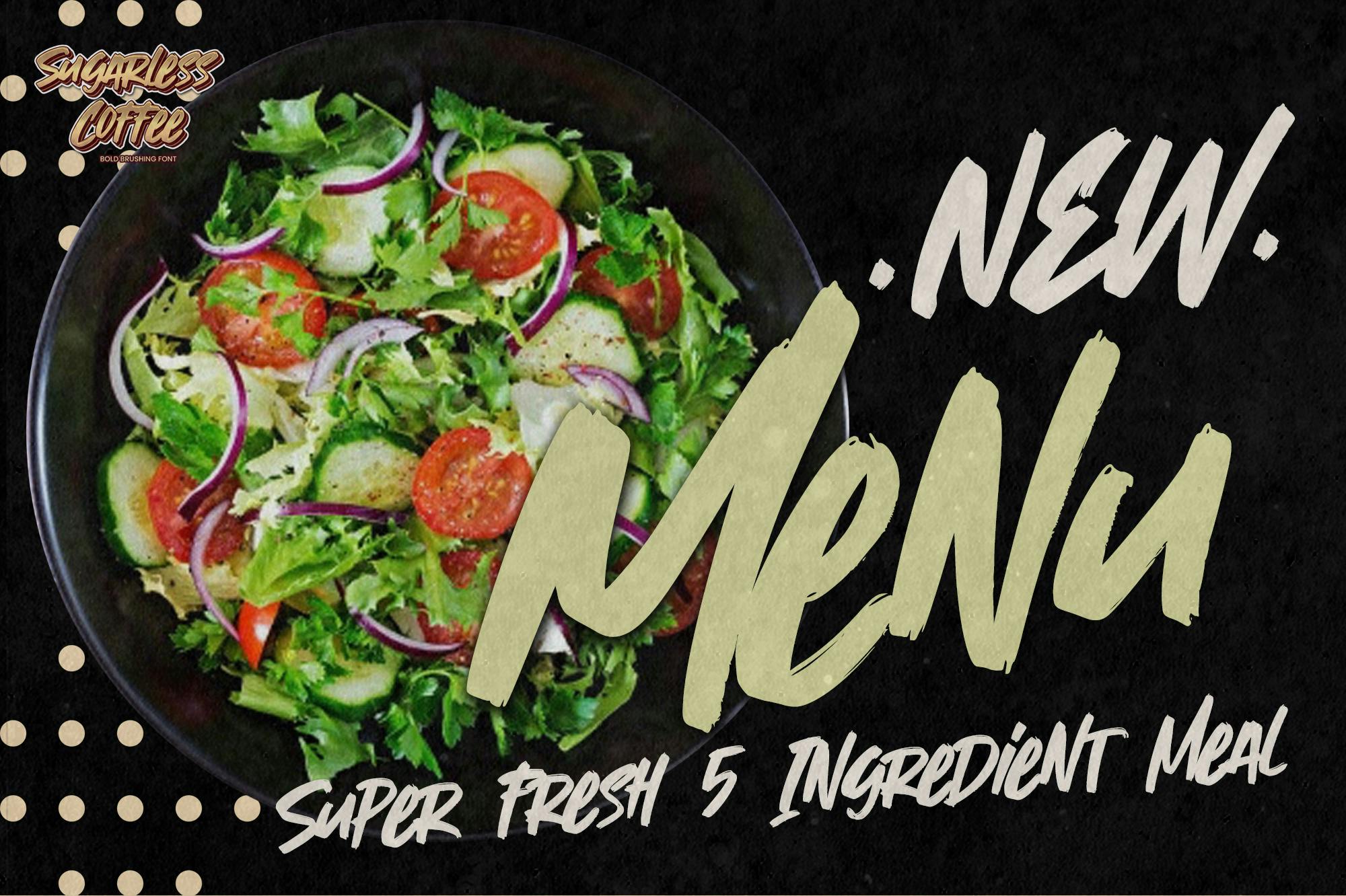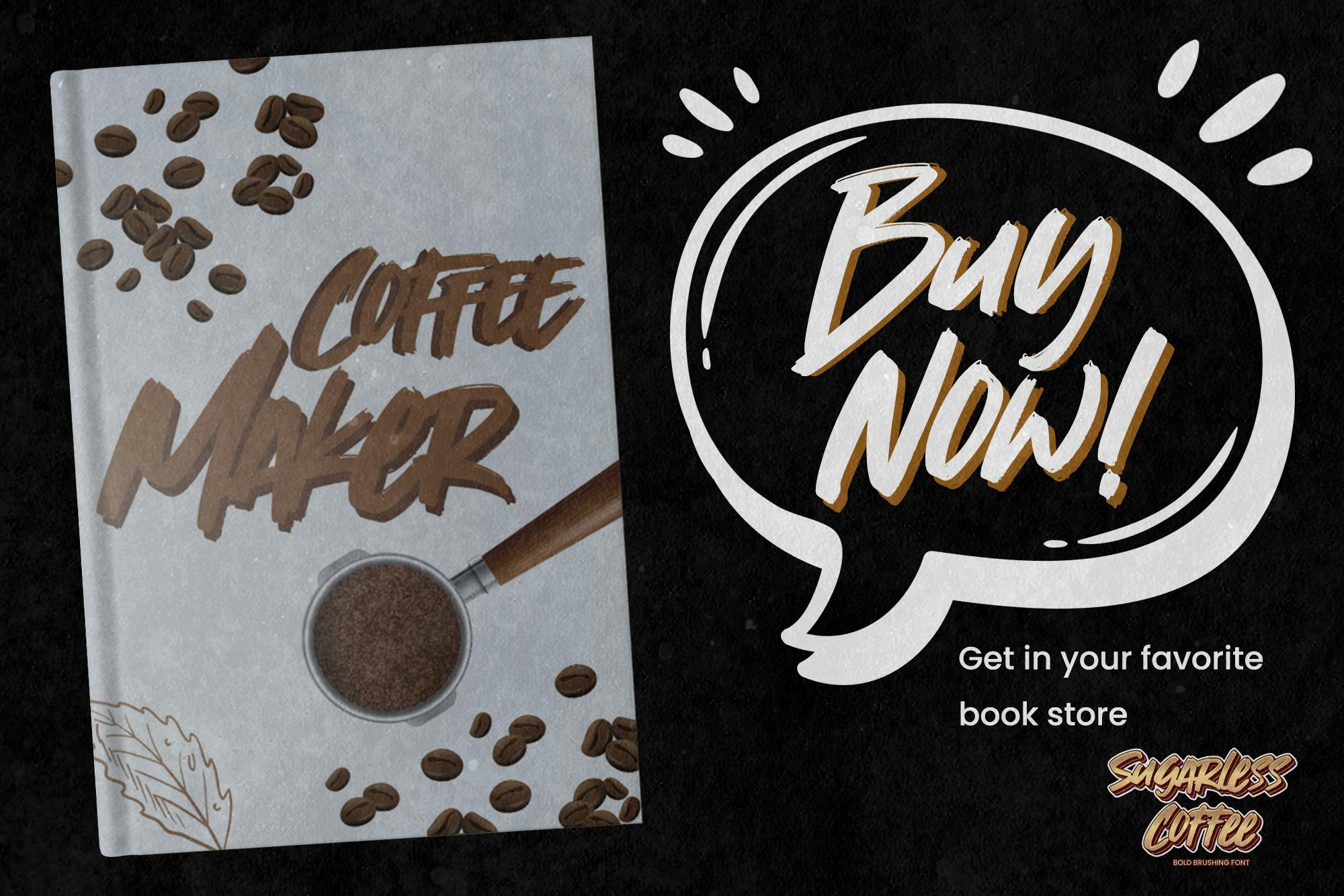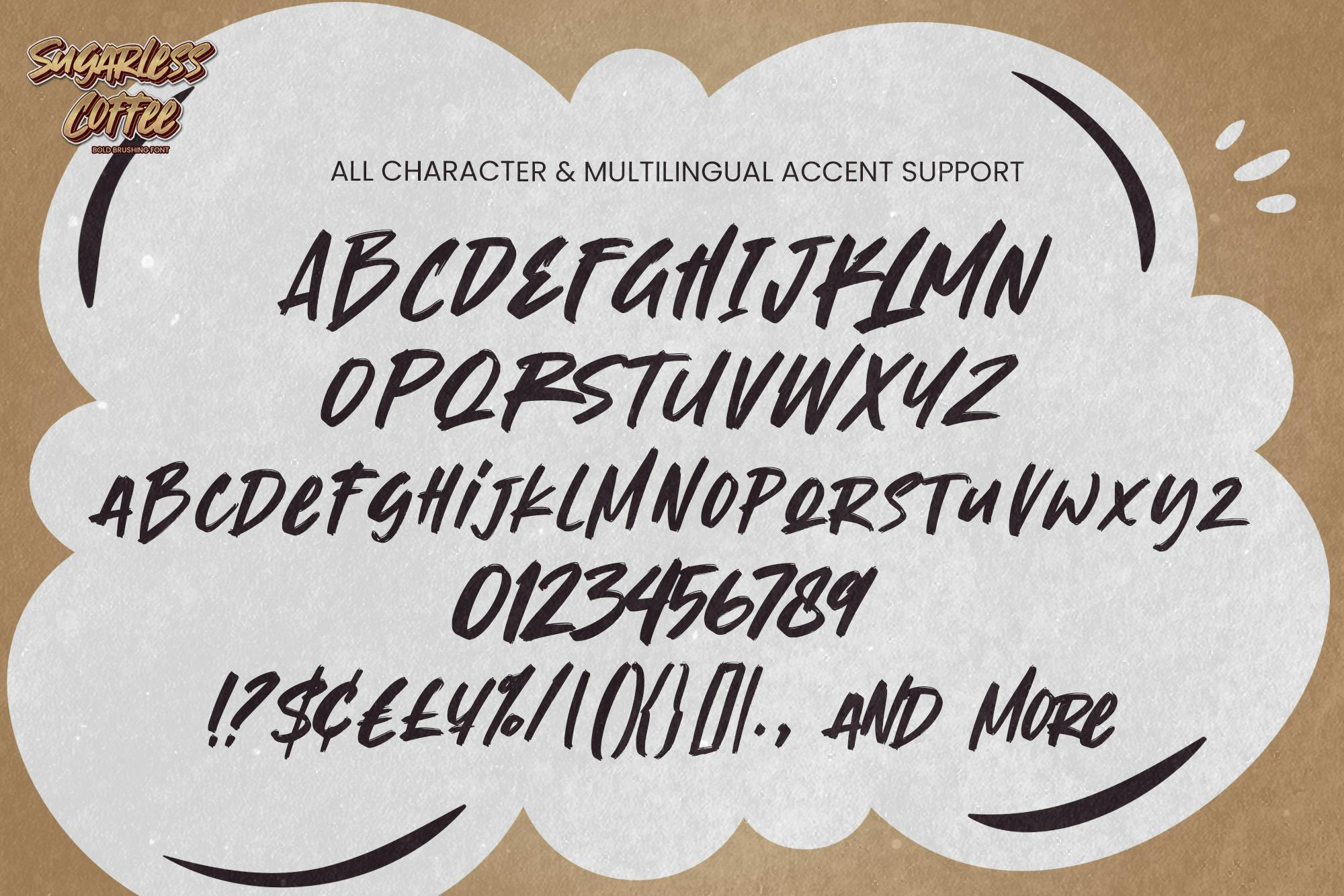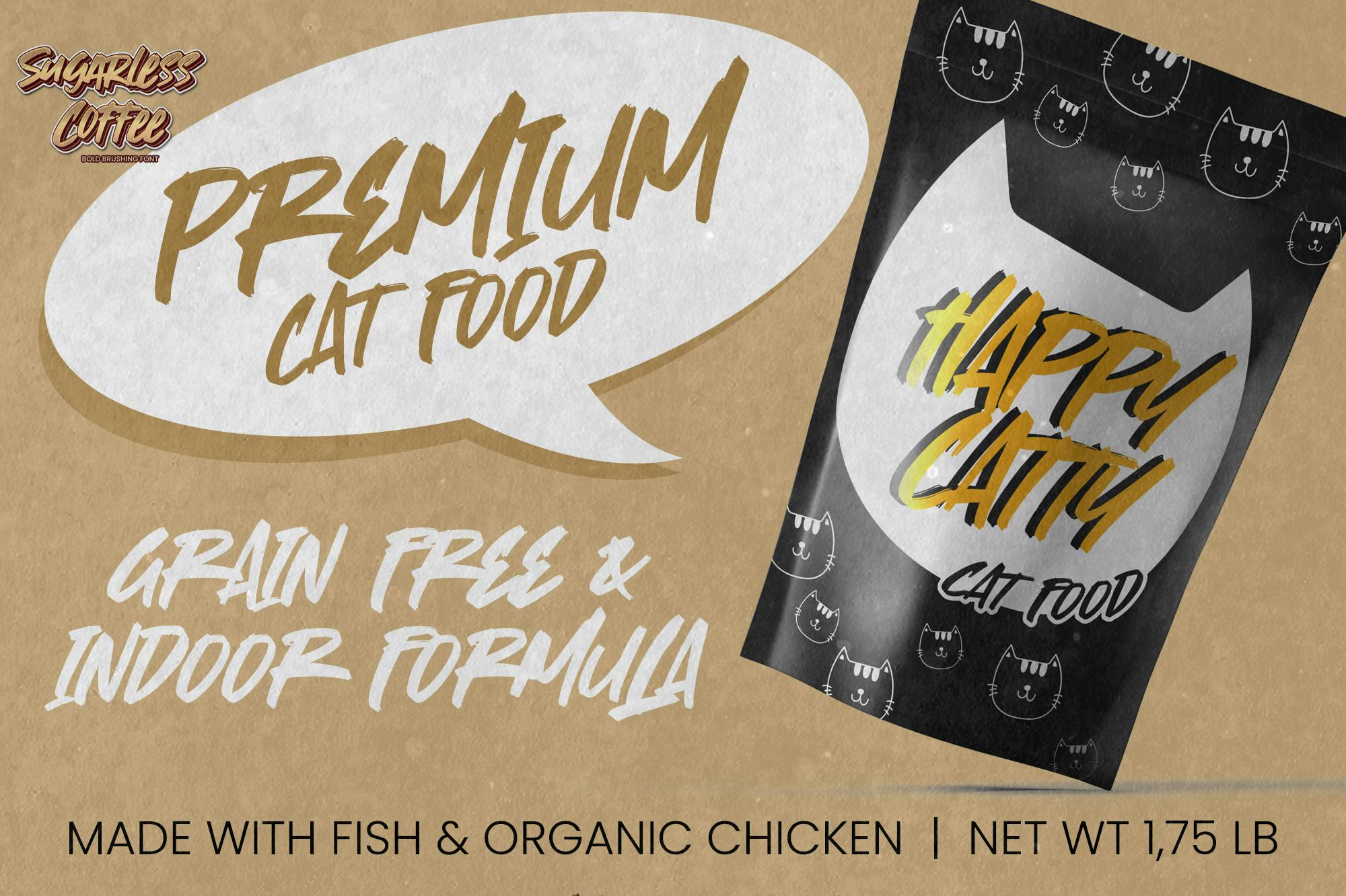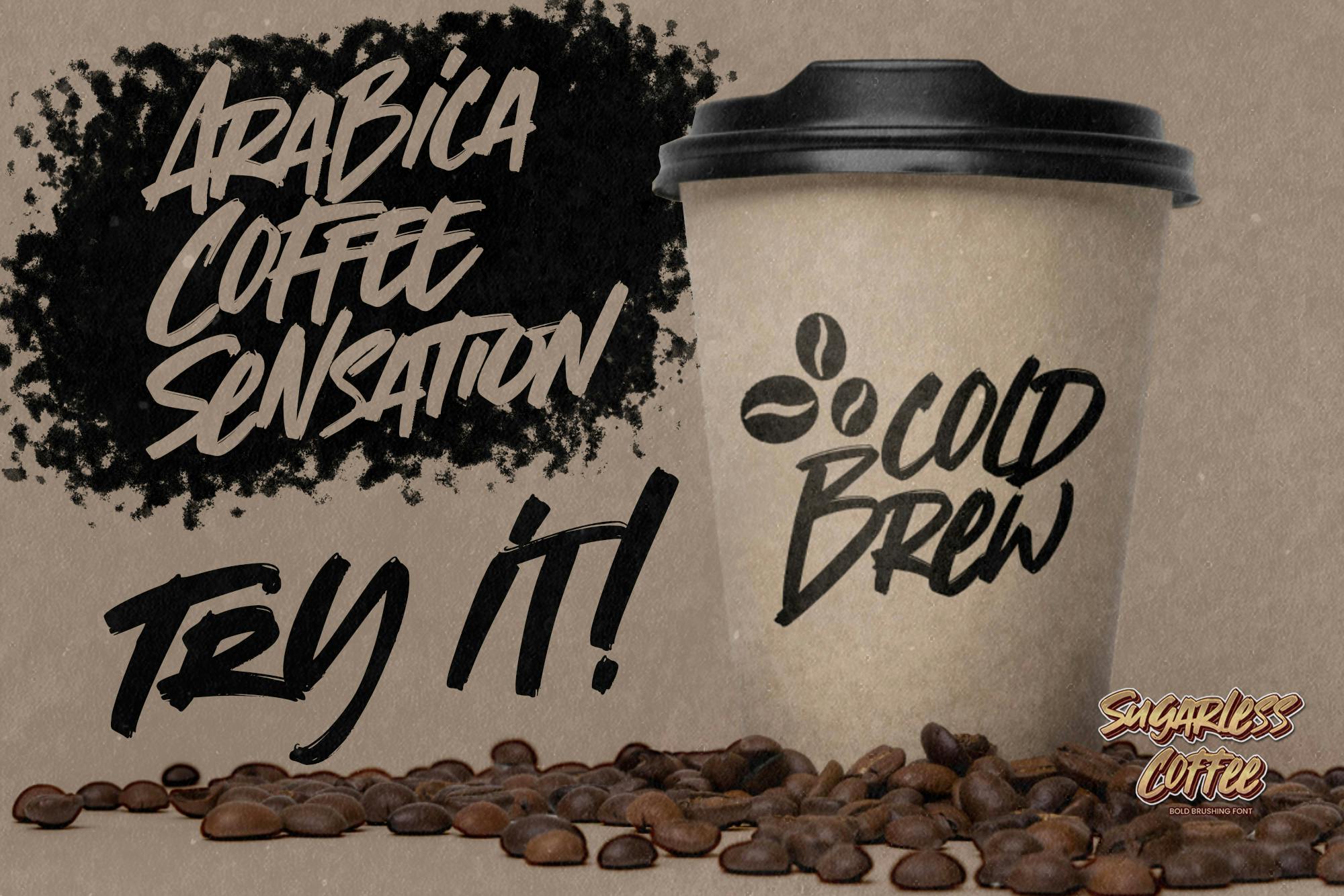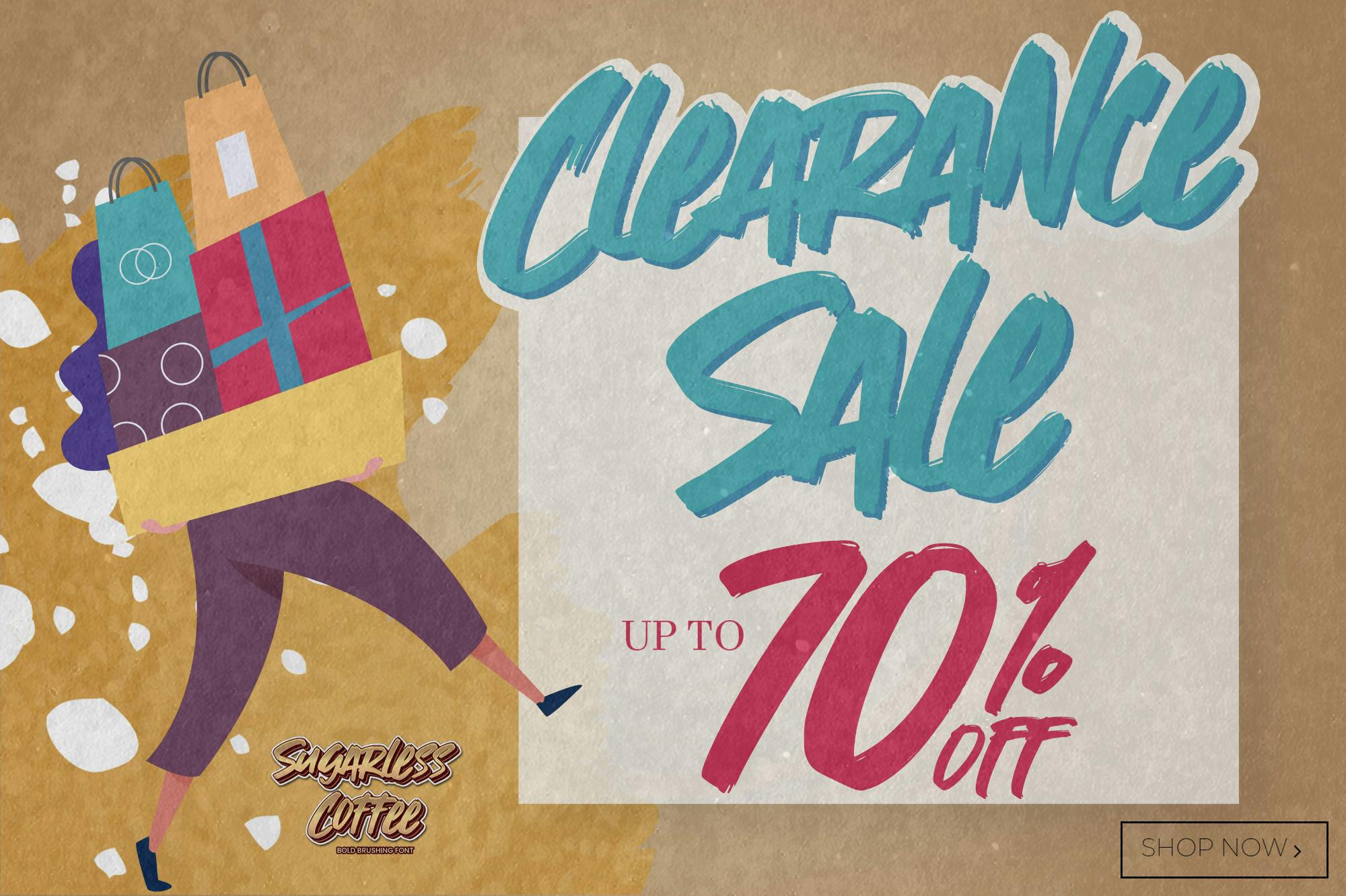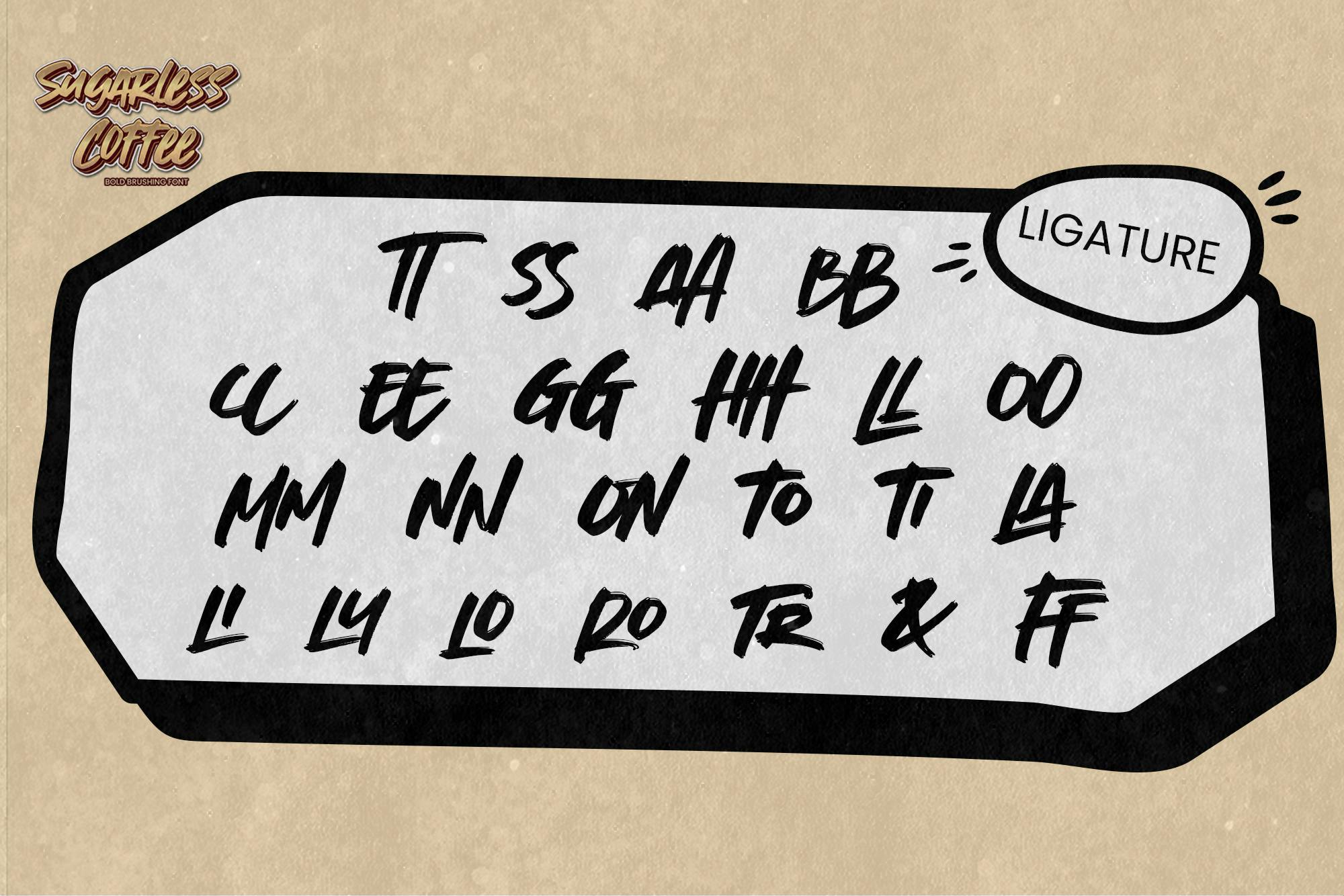
سلام به همه، خوشحالیم که محصول جدید خود را معرفی میکنیم: Sugarless Coffee - فونت برجسته و براشینگ، الهامگرفته از عنوان یک پوستر ورزشی و با انرژی بالا طراحی شده است.
فونت Sugarless Coffee با نوانسهای قوی و چالشبرانگیز، بسیار مناسب برای عناوین، تایپوگرافی، پوسترها، مجلات، بروشورها، بستهبندی، وبسایتها و بسیاری از نیازهای طراحی شماست که طراحیهای شما را مدرن و حرفهایتر میکند.
این فونت الهامگرفته از سبک لوگو و ترکیب با سبک صنایع دستی است که نیازهای طراحی شما را برای نقل قولها، تمهای ورزشی، لوگوتایپ، ووردمارک و غیره برآورده میکند. این فونت دارای ویژگیهای متعدد OpenType و پشتیبانی از چند زبان است.